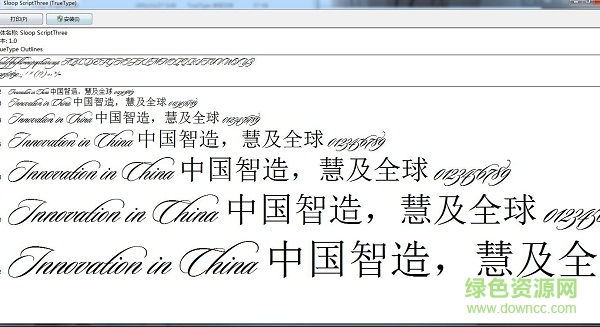
軟件介紹 軟件標(biāo)簽: sloop字體 花體字體 sloop scriptthree.ttf字體是一款多見于裝飾設(shè)計的精美花體字體,線條流暢灑脫,字形張揚,適合用在時尚雜志封面、影視海報等封面,歡迎有需要者在本站下載!廣告字體的設(shè)計根據(jù)廣告主題的要求,極力突出文字設(shè)計的個性色彩,創(chuàng)造與眾不同的獨具特色的字體,給人以別開生面的視覺感受,將有利于企業(yè)和產(chǎn)品良好形象的建立。特色字體推薦符號字體socialico 授權(quán):免費軟件 WinAll大?。?5KB語言:中文socialico字體是一款獨特的符號字體,包括愛心、箭頭、分享標(biāo)準(zhǔn)、方向盤、加號等一系列符合,輸入字母和數(shù)字即可馬上轉(zhuǎn)變成符號,需要的朋友快來下載吧!字體的特征介紹字形變化中特點:(舊)—–嚴肅、端正、正式、中下載地址blessed day 授權(quán):免費軟件 WinAll, WinXP, Win7大?。?5KB語言:中文blessedday字體是一款優(yōu)雅好看的花體字體,字體華麗線條優(yōu)美,常常用于制造邀請函、精美的賀卡以及各類請柬等,喜歡這款字體的朋友還有在綠色資源網(wǎng)下載!花體字體特色1.粗細變化2.游絲 3.排版總的來說即為裝飾下載地址sloop字體安裝方法1.需要進行字體安裝方可調(diào)用字體2.將字體拖動到C:\Windows\Fonts文件夾進行安裝3.如若編輯器內(nèi)未顯示字體文件,可重新打開編輯器查看 軟件截圖 上一張下一張(1 / 1) 安裝詳細截圖 其他版本下載 標(biāo)題 大小 更新日期 下載 下載地址 電腦版 sloop scriptthree.ttf 點擊報錯 軟件無法下載或下載后無法使用,請點擊報錯,謝謝! 關(guān)閉報錯反饋 請描述您所遇到的錯誤,我們將盡快予以修正,謝謝! *必填項,請輸入內(nèi)容 本類最新 sounso beauty字體 spyced哥特英文字體 ttf版 zerodegrees字體 the next font ttf版 coolvetica font keep calm ttf 免費版 相關(guān)文章 讓手機通過ADSL寬帶上網(wǎng) STOP:Ox0000008E藍屏解決方法 電腦開機使顯示PRESS F1 TO RUN SETUP/PRESS F2 TO LOAD DEFAULT VALUES Windows 7系統(tǒng)無法安裝Deamon Tools虛擬光驅(qū) 教你修改關(guān)閉煩人的開機LOGO 根據(jù)ADSL指示燈判斷網(wǎng)絡(luò)故障 用戶評論 熱門評論 最新評論 發(fā)表評論 查看所有評論(0) 昵稱: 請不要評論無意義或臟話,我們所有評論會有人工審核. 字數(shù): 0/500 (您的評論需要經(jīng)過審核才能顯示)